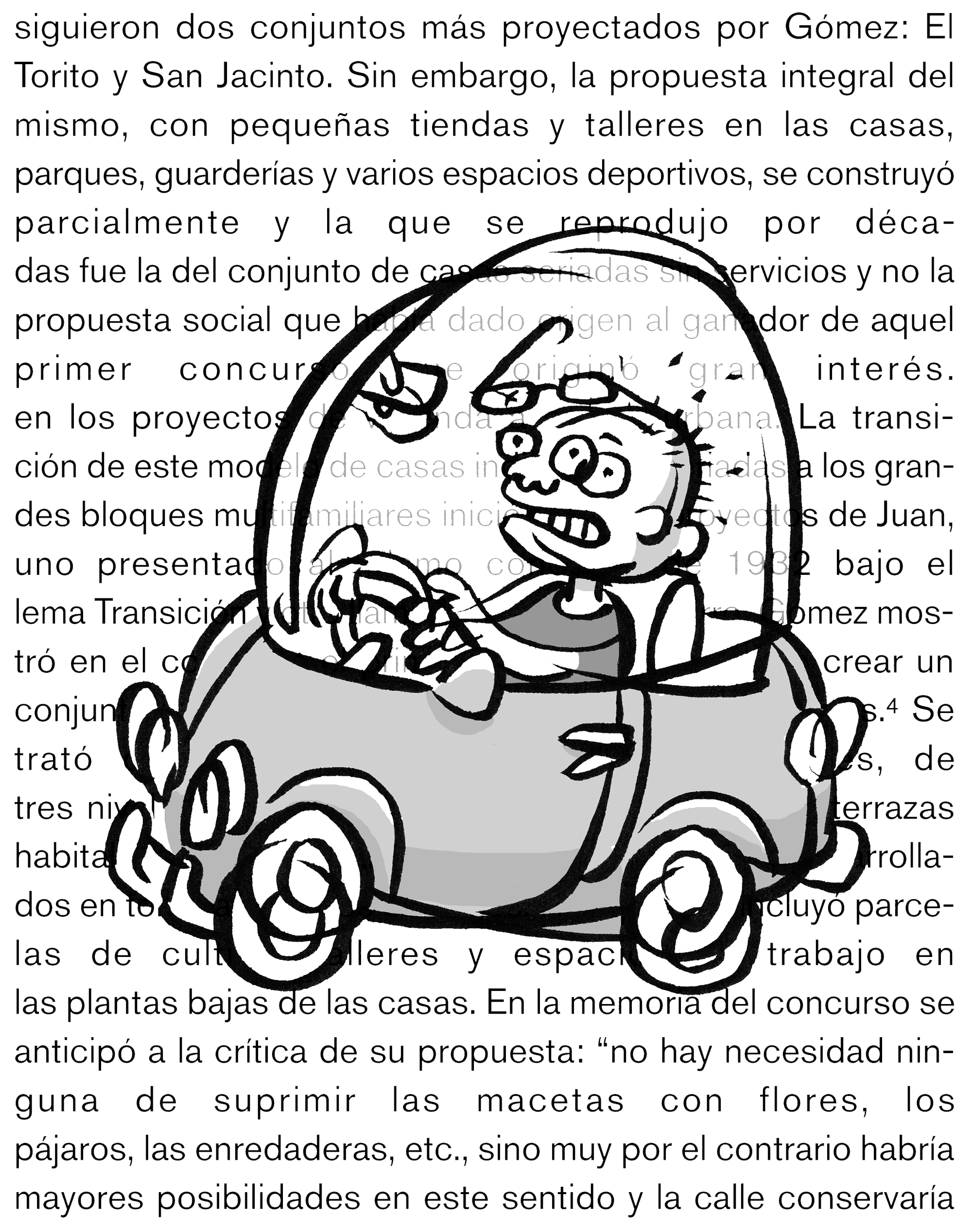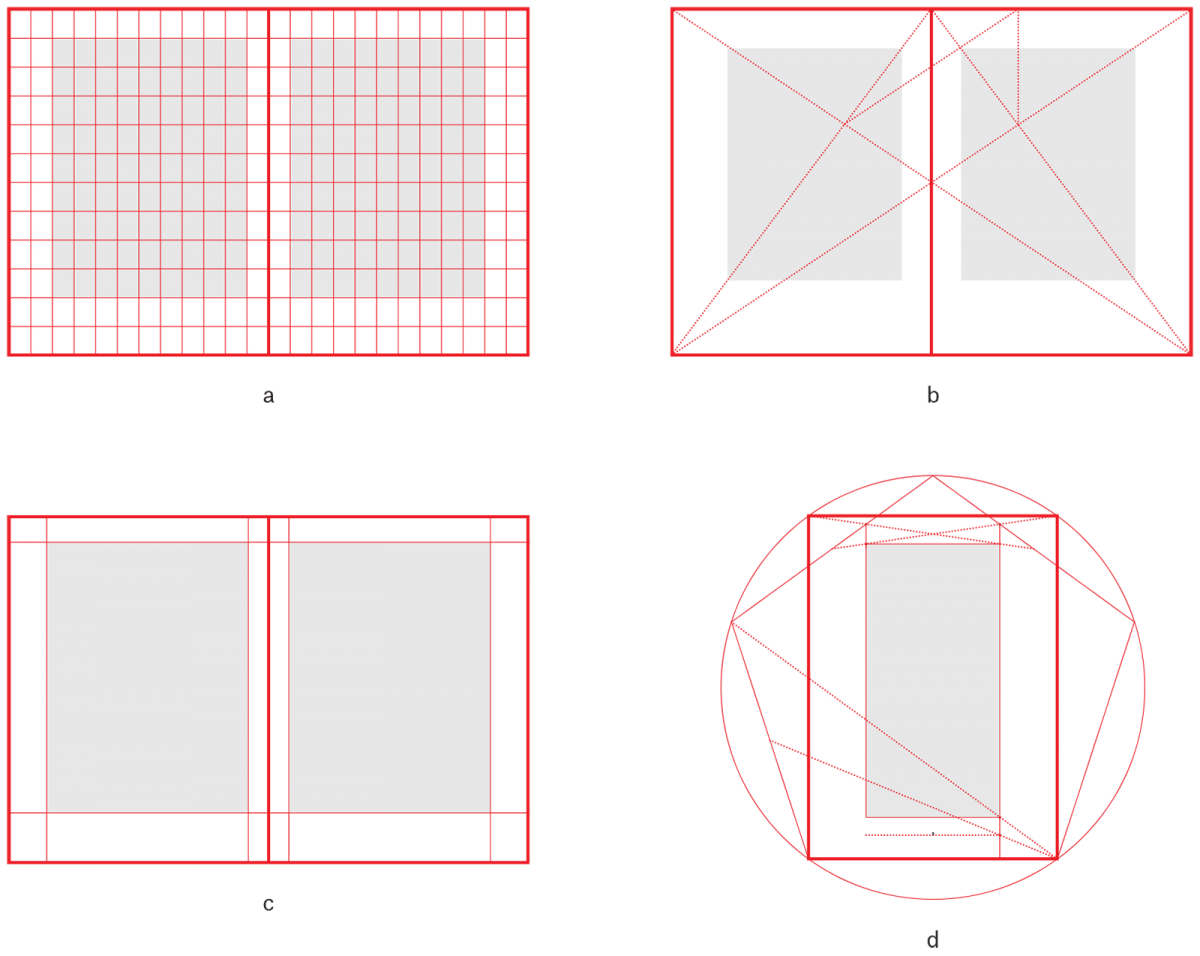
Tipografía para textos inmersivos: cuando lo esencial es invisible a los ojos. Segunda parte
Introducción
Leer un texto bien diseñado y compuesto es como manejar por un camino bien trazado y en buen estado. Ambas condiciones son igualmente importantes: es horrible manejar en una carretera con curvas mal trazadas o carriles muy angostos. Y un camino bien trazado pero con el pavimento en malas condiciones es también incómodo y peligroso. Con los textos pasa lo mismo. El trazo del camino equivale al diseño general de una caja de texto: la selección tipográfica, el cuerpo, la interlínea, la longitud de los renglones... y las condiciones del pavimento son como la calidad en la composición tipográfica. Un asfalto liso y limpio es como una caja con párrafos de un gris homogéneo, sin líneas demasiado abiertas o cerradas, ni callejones, dobles espacios, rosarios y una larga lista de “baches” tipográficos.
“[…] es horrible manejar en una carretera con curvas mal trazadas o carriles muy angostos. Y un camino bien trazado pero con el pavimento en malas condiciones es también incómodo y peligroso.”
Hace unos años mi esposa me preguntó por qué invertía tiempo cuidando detalles “que nadie ve”. Se refería a mi obsesión por definir los parámetros de justificación óptimos para una caja de texto. Le respondí que el objetivo de mi trabajo es precisamente que no se note. Me asumo como un especialista en la calidad del asfalto, cosa en la que no suele repararse, a menos que esté en malas condiciones.
Alguna vez escuché que “La tipografía puede ser de cualquier color, mientras sea negra”. Creo que para los textos de lectura inmersiva, 1 la tipografía puede ser de cualquier color, mientras sea “invisible”. La idea de la tipografía invisible no es nada nueva. En 1930, Beatrice Warde dictó al gremio de tipógrafos ingleses una conferencia llamada “Printing Should be Invisible”, publicada años después en un libro de ensayos titulado The Crystal Goblet: Sixteen Essays on Typography. 2 En este famoso texto, Warde hace una metáfora de la tipografía al compararla con una copa de vino y explica que es importante que ésta —la copa— sea “fina y transparente, como una pompa de jabón”, porque “toda ella ha sido creada con la finalidad de revelar, en vez de ocultar, las cosas bellas que puede contener”. 3 Es evidente que la tipografía no es invisible y su transparencia —la capacidad de actuar como un medio que no altere el significado, tono o intención del contenido— no puede ser absoluta. Quizá la tipografía podría pensarse conceptualmente más cerca de la transparencia que de la invisibilidad, ya que la transparencia, siendo visible, nos permite obviar la copa para ver el contenido, o dejar de ver la ventana para gozar del paisaje. Lo interesante es que en ciertas circunstancias, la tipografía funciona “en automático”, volviéndose invisible al lector, que se “conecta” en forma directa con el contenido sin reparar en el medio. Gerard Unger en su libro ¿Qué ocurre mientras lees? Tipografía y legibilidad, 4 dice que cuando el lector se encuentra inmerso en un texto, éste se vuelve invisible e incluso el objeto que lo contiene desaparece. Aun cuando estos conceptos son más que conocidos, vemos proliferar, incluso en ediciones de arte, cajas tipográficas mal compuestas, con grandes huecos entre palabras o renglones en los cuales es difícil ver dónde termina una palabra y empieza la siguiente. Esto puede destruir uno de los propósitos fundamentales de algunas piezas editoriales: comunicar un contenido de la manera más transparente posible. ¿Por qué pasa esto?
Por un lado pasa que los diseñadores no estamos entrenados para hacer trabajo invisible. Va en contra de nuestra “naturaleza”. Normalmente se nos enseña que la energía invertida en un proyecto debe tener como resultado una pieza vistosa, con un mensaje de gran impacto visual y original en el plano formal. Esto es indispensable para un gran espectro de trabajos de diseño, pero existen muchas piezas o partes de una pieza que deben funcionar de manera distinta. Claro que para muchos colegas es aburrida la sola idea de cuidar la calidad del asfalto, pero me pregunto si a alguno de ellos le gusta manejar por caminos en mal estado (excluyendo a quienes gustan de los rallies o de manejar con vehículos todo terreno a campo traviesa). No se trata de una cuestión de gusto, sino de necesidad.
Una vez que nos damos cuenta de esta necesidad, aún queda el problema de la solución técnica. Pensamos que al vaciar un texto en nuestros programas de edición, el resultado es automáticamente bueno, y esto que pensamos nos impide percibir lo que queda a la vista: que si dejamos que los programas de diseño “decidan” sobre la composición de textos, el resultado será, a juzgar por el resultado, mediocre. Hoy en día contamos con herramientas que nos permiten componer textos con mayor calidad y eficiencia que antes. La mala noticia es que no sabemos con exactitud cómo aprovecharlas. Antes se tenía más oficio pero herramientas más limitadas (tal vez se tenía más oficio porque éstas así lo demandaban). Ahora tenemos mejores herramientas pero hemos perdido el oficio. En el diseño editorial, los programas son tan “inteligentes” como los comandos que le damos. A veces sólo acabamos potenciando nuestra ignorancia.
Pero pongamos los pies en la tierra y hagamos una pregunta crucial: en términos prácticos (con una inversión de tiempo razonable) ¿vale la pena ser un nerd de la microtipografía e invertir tiempo en diseñar textos invisibles? En el supuesto de que lo que estamos buscando es lograr la máxima calidad en la composición de textos, mi respuesta es un rotundo “sí”. Casi siempre, la búsqueda de calidad implica mayor inversión de tiempo. En el caso de la composición de textos, veremos que usando las herramientas indicadas con los valores correctos —y de hecho sólo si se usan—, no solamente lograremos mejorar la calidad de nuestro trabajo, sino que lo podremos hacer con una inversión de tiempo menor que si no las usamos. En otras palabras: mayor calidad en menos tiempo, una situación de ganar-ganar. Además, en mi experiencia, cuidar la calidad en la composición de textos ha sido un factor de ventaja competitiva en el mercado.
Por una cuestión de extensión limitada, en este texto tocaré de manera superficial aspectos macrotipográficos de la caja de texto y su posición en la página (el trazo del camino) y profundizaré más en la microtipografía y la composición (la calidad del asfalto). Me enfocaré en el diseño de textos para lectura inmersiva justificados a ambos lados, aunque las herramientas que se explicarán también resultan útiles en otros tipos de composición. Por último, es importante tener presente que los ajustes están pensados para su aplicación en piezas impresas.
Aspectos que facilitan (o entorpecen) la lectura inmersiva
Hay tres condiciones necesarias para conseguir el efecto de “invisibilidad” en nuestras cajas de texto: la primera es una buena selección tipográfica, combinada con un buen equilibrio entre el cuerpo, la interlínea, el ancho de la caja, la ubicación de ésta en la página y el tamaño y proporciones del formato. La segunda es la microtipografía: sutiles ajustes de espacio entre caracteres y palabras que nos ayudan a obtener un gris uniforme en las cajas de texto. A veces, tales ajustes deben hacerse manualmente, por ejemplo, cuando detectamos un problema de acoplamiento (kerning) entre dos caracteres. Hay otros que podemos predeterminar para que sea el programa el que los ejecute de manera automática. Por último, es importante evitar errores en la composición de los textos, como callejones, rosarios, ríos, viudas, huérfanos, etc. El orden en el que se enlistan estas condiciones coincide con el orden en el que se trabaja: no tiene sentido concentrarse en la microtipografía si la caja de texto no está diseñada, y es poco recomendable cuidar en detalle las galeras sin tener bien tuneada la microtipografía.
Selección tipográfica
Hay diseñadores que trabajan con las mismas fuentes durante décadas y otros que gustamos de probar nuevos diseños con regularidad. Algunos dejan de usarse pronto y otros se vuelven parte importante de nuestra “paleta tipográfica”. Cada diseñador decide qué opción tomar y a cuál renunciar. En lo particular, disfruto de buscar, analizar y, si es posible, probar distintas fuentes para un nuevo trabajo.
Hablar de El-método-único-e-infalible-para-seleccionar-y-combinar-fuentes es, para decirlo en pocas palabras, ocioso. A veces la mejor opción para un proyecto es ridícula para otro. Sin embargo, hay algunas guías generales que pueden ayudarnos a tomar decisiones acertadas en este frente.
El concepto
Antes que nada, pienso que todas las decisiones de diseño deben ceñirse a un concepto rector, desde el formato, la encuadernación, los materiales y procesos, hasta los criterios compositivos, la paleta cromática y, claro está, la selección tipográfica, por mencionar sólo algunas. En ciertos círculos, decir que para un proyecto de diseño se usará la familia tipográfica Times New Roman es casi un chiste, pero existen varias piezas de diseño soberbias que la usan, como Weingart: Typography. My Way to Typography, escrito y diseñado por Wolfgang Weingart 5 o Welt aus Schrift, diseñado por Michael Heimann y Hendrik Schwantes, 6 uso que justifican por relaciones históricas con el contenido o incluso como una toma de postura de diseño. En cualquier caso, hay que tener mucho cuidado con las reglas que se toman como dogmas: después de servirnos como una sólida base para nuestra práctica, las reglas inquebrantables pueden convertirse en una venda que nos impide ver caminos nuevos.
El aspecto legal
Hoy en día existen plataformas que nos dan acceso gratuito a más fuentes de las que probablemente tendremos posibilidad de usar en nuestra vida profesional, todo de forma legal. También están los esquemas de renta en plataformas como Skyfonts, de Monotype; Typekit, de Adobe, o Fontstand, que para muchos colegas resultan muy prácticas y económicas, ya que permiten usar muchos diseños de primera línea por una fracción del costo que tiene la adquisición de la licencia de uso “tradicional” (aunque a veces no se incluyen las fuentes más exquisitas de una familia). Si esto no es suficiente (y para mí no lo es), pueden adquirirse las licencias directamente de casas tipográficas o distribuidoras. Por último, es posible comisionar el diseño de fuentes o familias enteras personalizadas. Sea cual sea el caso, es importante que las licencias de uso de las fuentes que usamos —y por cuyo uso cobramos— sean adquiridas de forma legal. El tipógrafo mexicano Cristóbal Henestrosa abunda más sobre esquemas de distribución y aspectos legales en el libro Cómo crear tipografías. 7
La necesidad
Cada proyecto editorial tiene necesidades tipográficas particulares, que podemos clasificar en tres grandes bloques: las constructivas, las funcionales y las expresivas. Las primeras se refieren a los aspectos técnicos, es decir, la disponibilidad y compatibilidad de formatos con el equipo y sustratos que se usarán para la producción del impreso. Las necesidades funcionales son el set de caracteres —que debe ser suficiente para componer el texto en cuestión—, 8 la legibilidad y el rendimiento. Finalmente, en las necesidades expresivas podemos incluir la comunicación del espíritu del contenido, desde términos relativamente subjetivos, como amabilidad, seriedad, elegancia... hasta conexiones históricas, geográficas, de estilo o incluso de género. El secreto consiste en jerarquizar las necesidades a cubrir con base en el concepto rector de la publicación. Por ejemplo, en un proyecto podemos considerar indispensable que la familia seleccionada sea diseñada por una mujer, mientras restamos importancia al rendimiento. En un diseño para periódico, lo más razonable es buscar entre las familias diseñadas para el sustrato sobre el cual se imprimirá, que tiene una ganancia de punto mayor que los papeles con recubrimiento. Si se busca originalidad ante todo y las condiciones económicas y disposición de tiempo lo permiten, se puede crear una familia tipográfica de cero, para uso exclusivo del cliente.
Es claro que hay muchísimas opciones tipográficas para textos de lectura inmersiva, cada una con sus fortalezas y debilidades. Para efectos de este artículo, mencionaré algunas de las características más comunes de las fuentes usadas para este tipo de lectura. Primero, es más probable que nos encontremos con fuentes con patines (serifs) que sin ellos (en novelas y periódicos, el dominio de las fuentes con patines es abrumador, pero en algunas revistas podemos encontrar mayor equilibrio entre ambos estilos); los patines son relativamente finos en lugar de egipcios (con notables excepciones, como la Chaparral de Carol Twombly); también veremos que rara vez se usan fuentes muy pesadas o demasiado ligeras, con un ancho normal, en lugar de diseños condensados o extendidos. La altura x 9 va de lo modesto a lo moderado.
Características comunes en fuentes usadas para composición de textos para lectura inmersiva.
En años recientes, César Puertas y su equipo ha trabajado en la medición de varios parámetros de fuentes, de manera que podamos hacer una selección tipográfica basada en esos datos. 10
La caja de texto
Una vez seleccionada la fuente tipográfica podemos pensar en la caja y su posición en la página. Desde el análisis de incunables hasta los clásicos de los siglos xx y xxi, como Müller-Brockmann 11, Bringhurst 12, De Buen 13, Hochuli 14 o Bosshard 15, podemos encontrar inspiración y explicaciones detalladas de muchos sistemas distintos. En lugar de lo que sucede de la caja de texto hacia afuera, me concentraré en lo que sucede hacia adentro, aunque ambas cosas están íntimamente relacionadas.
a. Escala universal, b. Método de Van der Graaf, c. Escala modular y d. Geometría.
Los parámetros o ejes que dan forma a una caja son: la selección tipográfica, el cuerpo, la interlínea y el ancho y profundidad de la caja. Estos cinco parámetros están interconectados: si modificamos el cuerpo es probable que tengamos que ajustar la interlínea y el ancho de la caja. Si queremos una interlínea cerrada, tal vez sea conveniente no abusar de un ancho de caja demasiado generoso. Una caja angosta requiere menos interlineado que una ancha, a menos que los párrafos tengan muy pocas líneas... Por fortuna, la tipografía no es una ciencia exacta: no hay una solución única a un problema determinado, sino un rango de valores aceptables para resolver el problema. Es como en el tiro con arco: el centro de la diana es más grande que el diámetro de una flecha. Mientras nuestra propuesta esté dentro del “centro de la diana”, podemos estar tranquilos: los requerimientos estarán cubiertos.
El cuerpo
A la distancia entre los límites inferior y superior del rectángulo que contiene un glifo se le denomina cuerpo, lo que la gente común y corriente llama “tamaño de la letra” 16, y es uno de los factores a los que el lector es más sensible. Rara vez me he encontrado con clientes que pidan ajustar la prosa o la interlínea, pero varios han solicitado “un tamaño de letra grande”, pensando en los lectores de edad avanzada. Es importante mencionar que varias fuentes, aún cuando se compongan con el mismo cuerpo, parecen tener distintos tamaños. Esto se debe a que las distintas familias tipográficas “usan” de manera distinta el espacio mediante variaciones en las proporciones verticales. Así, una letra “a” de 10 puntos (pt) en Minion se ve de un tamaño muy distinto a una “a” en Helvética del mismo cuerpo, ya que la altura x es más pequeña en la primera que en la segunda. Estas variaciones en las proporciones influyen no sólo en el cuerpo sino en la interlínea. Una fuente puede sentirse cómoda con una relación cuerpo/fuerza17 de 10/12 pt, mientras que para otra fuente puede ser insuficiente. El cuerpo que decidamos usar debe ser cómodo para el lector previsto y ha de tomar en cuenta la distancia a la que se leerá el texto.
Ancho y profundidad de la caja
Bringhurst 17 señala que el ancho ideal es de 66 caracteres (cc) por línea 18. De Buen menciona distintos valores dependiendo de la habilidad de los lectores, a los cuales divide en altos lectores (los que tienen mucha soltura en la lectura) y bajos lectores (los menos experimentados).19. Para los primeros indica que el ancho óptimo es de 60 cc, mientras que el mínimo es de 45 y el máximo de 80. Para los bajos lectores el óptimo se ubica en los 45 cc, con mínimo de 34 y máximo de 60. Si bien en algunos textos breves (como en los artículos de revista) podemos tener unos 35 cc por línea, el rango de caracteres por línea para textos más largos debe ser de entre 50 y 80 cc. En cualquier caso, hay que considerar que mientras más angosta es la caja de texto, tendremos más problemas con líneas abiertas.20 El ancho de la caja y su profundidad tienen una relación estrecha con la interlínea: si tenemos una caja angosta, requeriremos menos interlínea. En cajas muy anchas se vuelve necesario aumentar la interlínea, ya que el ojo necesita un “pasillo” generoso entre los renglones para no errar el inicio de la siguiente línea, a menos que tengamos muy pocas líneas, en cuyo caso el ojo depende menos de la interlínea y se apoya más en los bordes superior e inferior de la caja.
Interlínea
En mis épocas de estudiante universitario, mi maestra de diseño editorial decía que la “regla” es que la interlínea debía corresponder a 20% del cuerpo. O sea que si éste era de 10 pt, aquella debía ser de 2 pt, resultando en una relación cuerpo/fuerza de 10/12 pt. Resulta curioso que en varios programas de autoedición, este 20% aparece como valor por omisión. Esta fórmula funciona en algunos casos, pero es difícil defenderla en muchos otros, ya que, como hemos visto antes, este porcentaje puede ser excesivo o insuficiente, dependiendo de nuestra selección tipográfica o el ancho de la caja. Otro argumento en contra del famoso “20%” es que puede generar valores de interlínea con fracciones decimales de punto (por ejemplo, si nuestro cuerpo es de 11 pt, la interlínea queda de 2.2 pt), lo cual puede causar escozor a ciertos tipógrafos que gustan de estructurar las páginas con picas y puntos sin fracciones.
Ir a la segunda parte de este artículo:
Tipografía para textos inmersivos: cuando lo esencial es invisible a los ojos. Segunda parte
David Kimura holds a degree in Graphic Design from the Universidad Iberoamericana (Mexico) and a postgraduate degree in Visual Communication from the Hochschule für Gestaltung und Kunst Basel. He was a founding partner of the firms Kimera and Bésame mucho. Since 2005 he has worked with Gabriela Varela specializing in typography and editorial design. They have designed for publishers in Mexico and Europe and their clients include Editorial Arquine, Editorial RM, Museo Nacional de Arte, Fomento Cultural Banamex, Museo Frida Kahlo, Museo Diego Rivera Anahuacalli, Conaculta, INBA, Esrawe Studio, bgp arquitectura, Fundación CIAC and Emblem. He is the author of the typefaces Plasma, Sofía and Chayote. He has also collaborated as designer or art director in the projects Gandhi (with Gabriela Varela, Cristóbal Henestrosa and Raúl Plancarte), Balduina (with the Círculo de Tipógrafos) and Mayathán (with Verónica Monsivais and Ma. de los Ángeles Suárez, under the direction of André Gürtler). His work has been published in books and specialized magazines in Mexico, the United States, Spain, Argentina and Japan. He has received several awards and recognitions from AIGA, Type Directors Club of New York, Type Directors Club of Tokyo, Kasseler Fotoforum, a!, Trama Visual, Quórum, and the Instituto Nacional de Bellas Artes. He has been teaching since 2001 and since 2006 he has been a professor in the Master’s Degrees of Typographic Design and Editorial Design at the Centro de Estudios Gestalt de Veracruz.
- Aquella que practican los lectores de textos de extensión regular o larga, por ejemplo, los que leemos en novelas, libros de texto o artículos de fondo en periódicos y revistas. ↩
- Warde, Beatrice, The Crystal Goblet: Sixteen Essays on Typography. (Jacob, H., ed.) Londres: Sylvan Press, 1955. ↩
- Warde, Beatrice, The Crystal Goblet. Londres: 1932, en “ ‘La copa de cristal, por Beatrice Ward’ ”, Unos tipos duros. Teoría y práctica de la tipografía. (Blog). Recuperado de: http://www.unostiposduros.com/«la-copa-de-cristal»-por-beatrice-warde/ ↩
- Unger, Gerard, ¿Qué ocurre mientras lees? Tipografía y legibilidad. Valencia: Campgràfic, 2009. ↩
- Weingart, Wolfgand, Weingart: Typography. My Way to Typography. Baden: Lars Müller Publishers, 2000. ↩
- Kühnel, Anita; Lailach, Michael y May, Jan, Welt aus Schrift. Das 20. Jahrhundert in Europa und den USA. Colonia: Kunstbibliothek Staatliche Museen zu Berlin, Verlag der Buchhandlung Walther König, 2010. ↩
- Henestrosa, Cristóbal, Meseguer, Laura y Scaglione, José, Cómo crear tipografías. Del boceto a la pantalla. Madrid: Tipo e, 2012, pp. 115-127. ↩
- Además del set de caracteres, hay que considerar la estructura y extensión del texto. En un documento con notas al pie de página, sobre todo si son profusas y muy extensas, es recomendable escoger una familia equipada con variantes ópticas para cuerpos pequeños. ↩
- Distancia entre la línea de base y el borde superior de las letras minúsculas que carecen de ascendentes, como a, c, e, m, n, o, r, s, u, v, w, x y z. ↩
- Puertas, César, “Selección tipográfica por parámetros”. Conferencia. (Archivo de video). México, Secretaría de Cultura. Recuperado de: https://interfaz.cenart.gob.mx/video/tipos-latinos-2014/ ↩
- Müller-Brockmann, Josef, Sistemas de retículas. Un manual para diseñadores gráficos. Barcelona: Gustavo Gili, 2012. ↩
- Bringhurst, Robert, Los elementos del estilo tipográfico. México: Fondo de Cultura Económica, 2014. ↩
- De Buen, Jorge, Manual de diseño editorial. S. L. Gijón: Ediciones Trea, 2008. ↩
- Hochuli, Jost y Kinross, Robin, El diseño de libros. Práctica y teoría. Valencia: Campgràfic Editors sl, 2005. ↩
- Bosshard, Hans Rudolf, Der typografische Raster. Sulgen: Verlag Niggli AG, 2000. ↩
- En la era de los tipos de plomo, el cuerpo era algo físico, que podía palparse. En la era digital, el “rectángulo” sigue existiendo, sólo que es una descripción matemática, al igual que el contorno de los glifos. Por esta razón, en las fuentes digitales es posible trabajar con interlínea negativa, o modificar el cuerpo en fracciones de punto. ↩
- Bringhurst, op. cit., p. 35 ↩
- Si bien no leemos caracteres sino palabras, prefiero definir los anchos de caja en caracteres, porque me parece que esta “unidad de medida” es más exacta que las palabras. Además, dependiendo del idioma, las palabras tienen promedios de caracteres distintos. ↩
- Las líneas abiertas son los renglones en los cuales el espacio entre las palabras es excesivo y generan huecos blancos en el párrafo. En las líneas cerradas sucede lo contrario: el espacio entre las palabras es demasiado estrecho. ↩